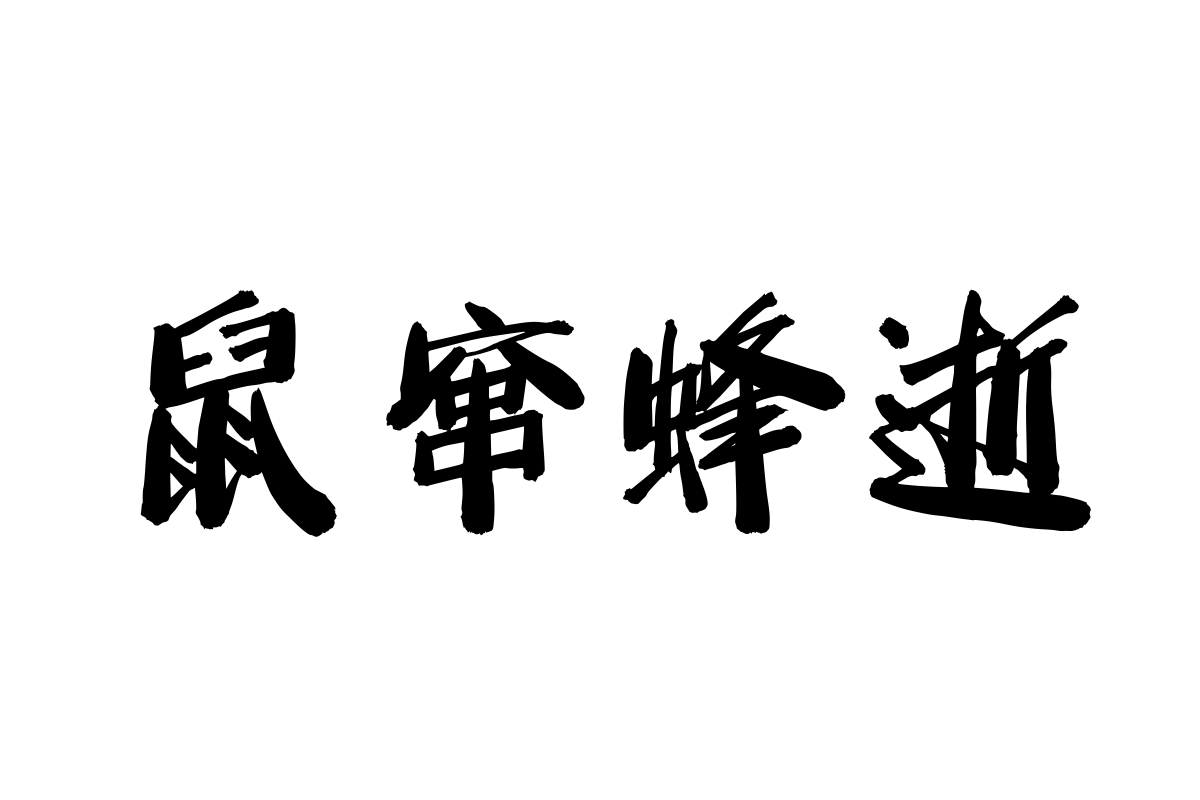
汉仪迪升浪浪体是一款具有现代感和时尚感的字体,其笔画流畅、字形优美。这款字体适合用于广告设计、包装设计、网站设计等领域,能够提升整体视觉效果,使作品更具吸引力。
汉仪迪升浪浪体的笔画粗细适中,既有力度又不失柔美。它的字形结构紧凑,但不失灵动,给人一种轻松愉悦的感觉。这款字体的线条流畅自然,无论是书写还是阅读都显得非常舒适。
此外,汉仪迪升浪浪体还具有一定的可读性。它的字形结构规整,每个字的笔画都清晰明了,易于识别。这使得它在各种场合都能得到广泛的应用,无论是在印刷品上还是在电子屏幕上,都能够得到良好的展示效果。
总的来说,汉仪迪升浪浪体是一款非常适合现代设计领域的字体。它以其独特的风格和优美的字形赢得了广大设计师的青睐。无论是企业宣传、产品包装还是网页设计,都可以使用这款字体来提升作品的整体效果,吸引更多的眼球。